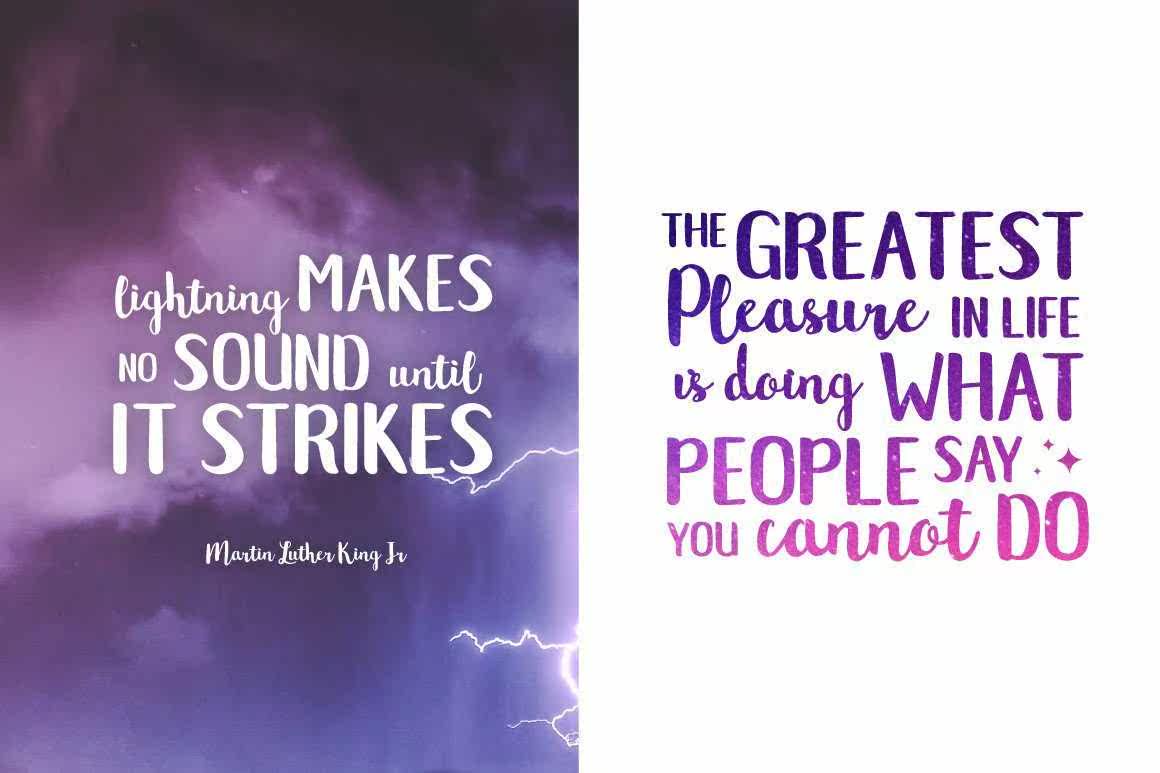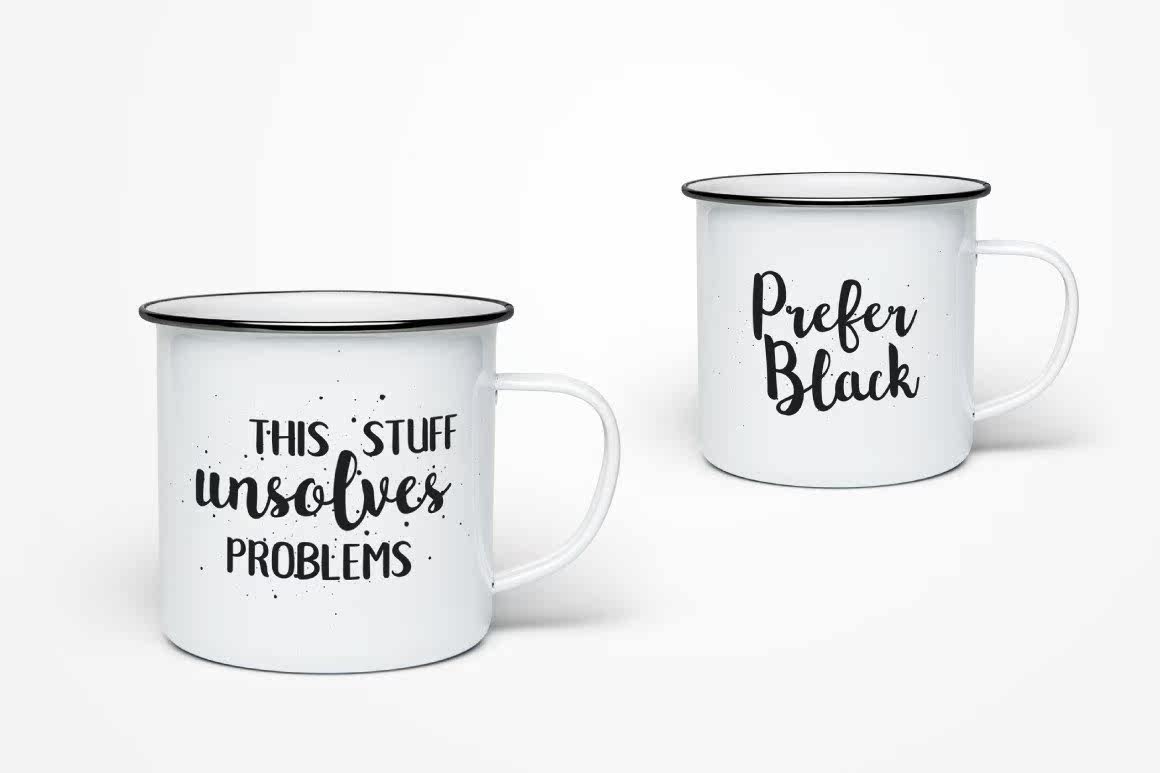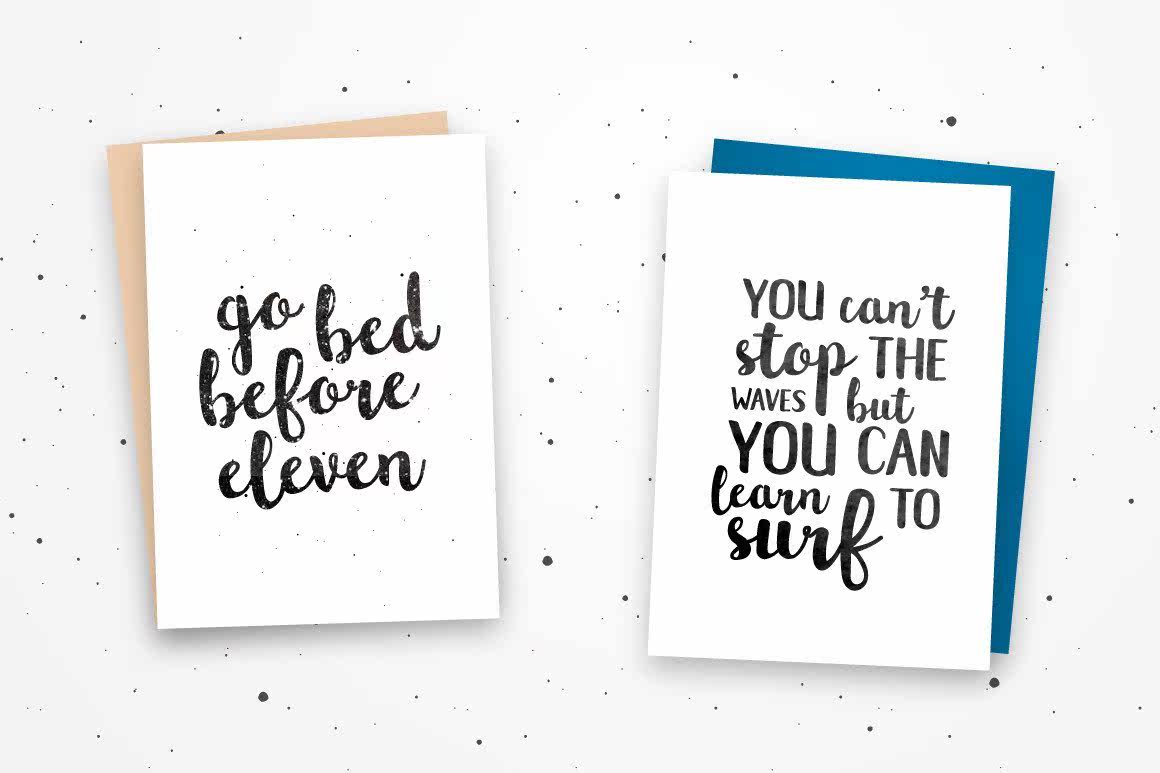
几周后,AgoidedTotakealeApa和CreateMyFirstFont!我走到离家不远的工匠家附近,买了几支手写铅笔。在练习之后,我用了一种看起来很完美的粗制滥造的脚本样式,开始把它变成一个数字字体。它削弱了插图,然后完美地通过字体的间距和字距进行了计算。我在这个字体上添加了一个版本,以便与脚本一起使用。我希望你喜欢它?几周前,我就决定了这样做leapandcreatemyfirstfont!我走到离家不远的工匠家附近,买了一支手写铅笔。在练习后,我用了一种看起来很完美的手写字体,开始将它改成数字字体。它削弱了插图,并完美地通过字体的间距和字距进行了计算。我在这个字体上添加了一个版本,以便使用该字体。你喜欢吗?